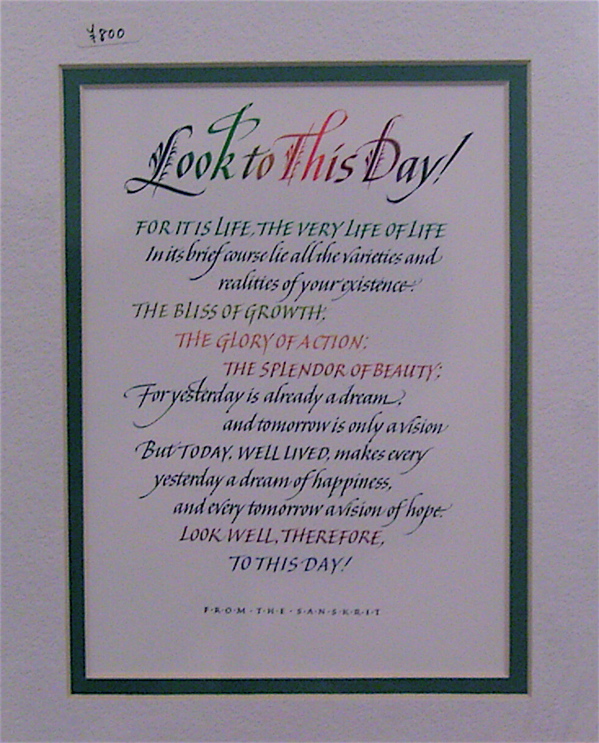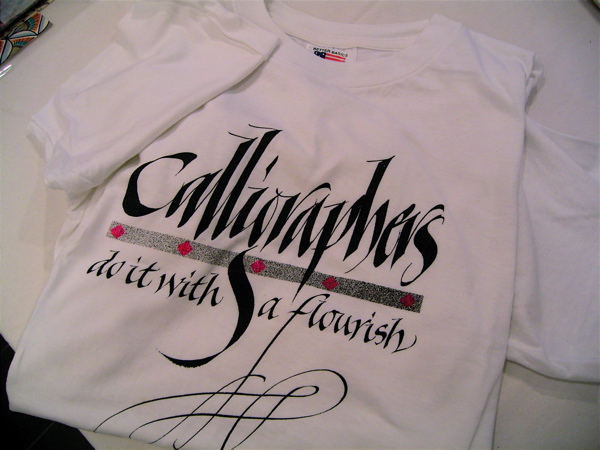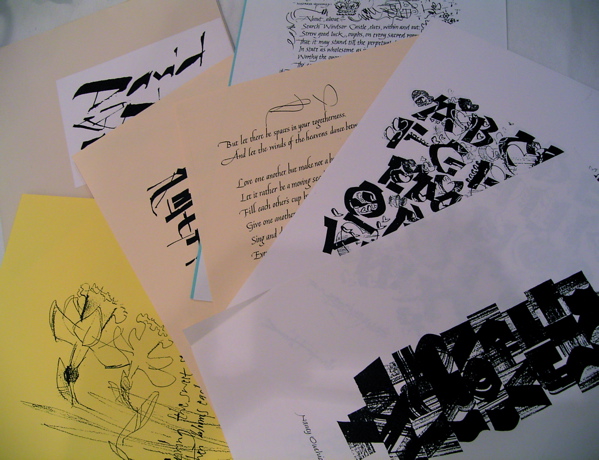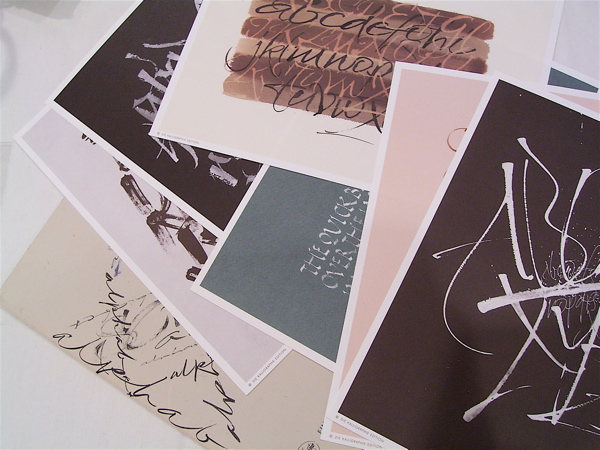
2.Sheila Waters 作品 カラー(プリント)、マット付き
カリを愛する世界中の人から尊敬を集めるシーラです。
その正確で美しい文字と装飾は、皆の憧れでもあります。
作品をまだ作ったことがない人もどうやってレイアウト
するのか・・・とか、どんな配色をするのか・・・などなど
著名なカリ人の作品は、必ずあなたを助けてくれます。
お嬢さん!本当です!
シーラは、有名カリ人ジュリアンのお母様〜
3.Sheila Waters 作品 ゴシサイズドイタリック(プリント)
シーラのゴシサイズドイタリックは、優雅で品があります。
国内では比較的人気のある書体でしょうか・・・。
日頃からお側に置いて、眺めましょう〜。
いつかこんな美しい作品が書けるかも・・・しれません
見れば見るほど・・・美しい〜。
4.Gottfried Pott 作品 フォルダ入り(プリント6枚)
こちらはドイツの巨匠!ゴットフリードの作品です。
ルーリングペンをカリ世界に広めたその貢献度は
計り知れません。
力強い作品を見れば、線そのものの勢い、美しさを
発見できるはずです!
5.David & Nancy Howells 作品
フォルダ入り(コピー10枚)
様々な文字のバリエーションが詰まっています!
自分自身の文字を探しているお嬢さん・・・、必見です。
作品を包んである紙までカッコイイ!さすが〜なカリ人です。
6.Tシャツ Denis Brown デザイン
最近日本でWSし続けていたDenisの若かりし頃・・・、
(今も若い?)のも・・・だと思います。
大き過ぎて着られなくても飾っておけるほど完成度高い
美しいカリグラフィーです
7.Skriptorium (ドイツ語版)
中世写字室について、そして
ギルディングなどの技法について
カラー48ページ
面白い縦長の本です。
中世の写本の世界と技術的なことや画材などのお話しが載って
います。
言葉がわからなくても、カラーページばかりなので、写真が
美しく眺めているだけでも飽きません〜!